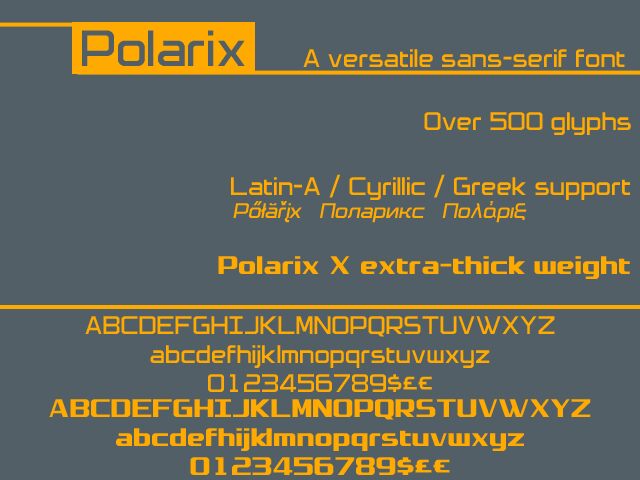
Polarix X di Alex Richards è un font display gratuito caratterizzato da silhouette alte e squadrate, bordi netti e intagli interni arrotondati che smorzano le forme evitando che risultino pesanti. Il contrasto tra le pareti esterne rigide e le aperture morbide conferisce alle lettere un ritmo compatto e meccanico, percepito come molto più studiato rispetto a un comune font geometrico.
Funziona perfettamente per titoli brevi, poster, copertine di album, miniature per lo streaming, packaging e concept di loghi. Le forme verticali dense e le giunzioni pulite conferiscono alle parole una forte impronta grafica, ideale per dare carattere a brand e titoli dove un classico font sans serif risulterebbe troppo anonimo.
Designer description: <p>It's Polarix, but with GIRTH.</p>